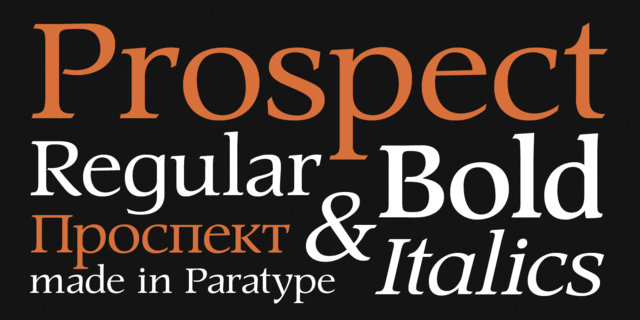
ПТ Проспект™ Оригинальная гарнитура, разработанная в 1997-2001 гг. (дизайнер Наталья Васильева). Антиква широких пропорций, свободного рисунка, со скошенными засечками. Рисунок шрифта частично воспроизводит рукописное начертание. Предназначен для акцидентного и титульного набора, преимущественно крупным кеглем.